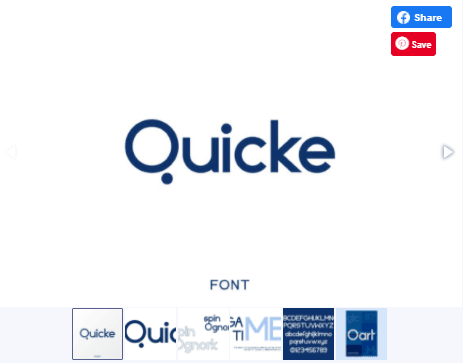
Quicke Font
Quicke - это уникальный и современный шрифт без засечек, идеально подходящий для заголовков, крупного текста, брендинга, логотипов и отображения. Шрифт добавит аккуратный и изящный акцент в каждую вашу красивую хитрую идею!